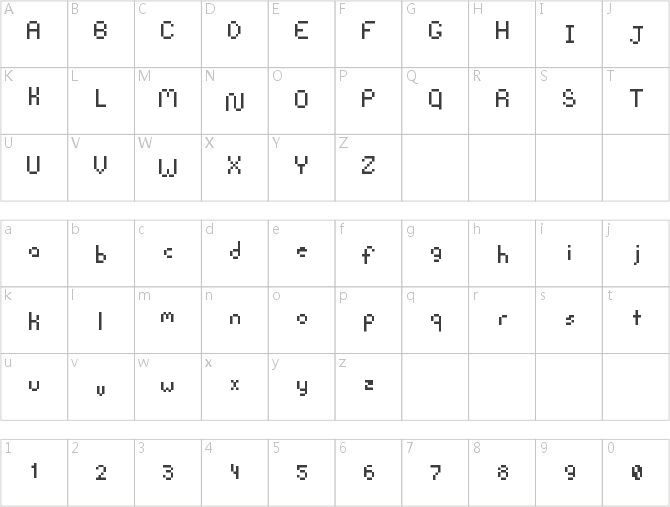
BitsyButton-v2-Regular 詳情頁(yè)
BitsyButton-v2-Regular字體字庫(kù)是一款讓人賞心悅目、百看不厭的英文字體,適合各類廣告和產(chǎn)品包裝設(shè)計(jì)應(yīng)用,字體大小0.12MB,格式為ttf字體,上傳用戶是woslxn,作者/版權(quán)方為未知